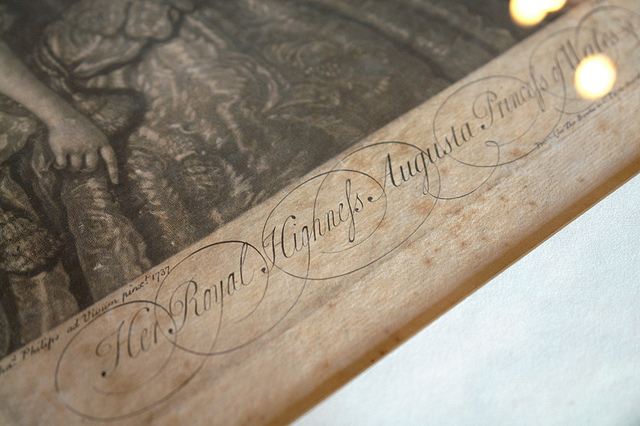
ich find das ja ganz schrecklich. da schreien dich riesige buchstaben in signalfarben an,
du weisst aber nicht wie du es zuordnen sollst, weil du es als parkhausbenutzer nicht so
gewohnt bist und suchst zusätzlich nach schildern. die farben sind eher verstörend,
wenn man ordentlich gestaltete infos sucht und sobald man sich um einen meter
verlenkt sieht das "leitsystem" nur noch nach komischen farbigen flächen aus.
wie ralf schon sagt es ist eher kunst. ich bin mir sicher in dem parkhaus knallt es öfter als vorher ;)
Das Parkhaus finde ich auch zu bunt und nicht besonders schön, und, wenn es dann noch nicht mal zweckmäßig ist, ist es natürlich eher ›suboptimal‹.
Aber die Sache mit dem Point of View finde ich schon cool. Das passt und ist schön gemacht m. E.
In einem Parkhaus kommt man aber auch nur aus einer stark begrenzten Zahl an Richtungen mit relativ leicht kalkulierbarem Blickwinkel auf derartige Beschriftungen zu, insofern ist das Perspektivenproblem wohl nicht sehr groß. Und ein schönes Parkhaus hab ich auch noch nie gefunden, da sind mir die grellen Farbklekser (die es auch so oft in derartigen Einrichtungen gibt) auch schon wurscht.
Hm. Eine kleine Schreibmaschinensammlung habe ich ja schon. Vielleicht sollte ich noch mal umsatteln auf meine alten Tage.
wobei ...
ich glaube ich würde ausrasten wenn ich in 'nem café wäre und da würde
jemand sitzen der wie wild auf seiner schreibmaschine herumhackt.
trotzdem eine schöne idee. paschulke, hurry up! du kannst der erste sein,
der das auf 'nem heidelberger tiegel macht. ;)
Schaut mal, was ich beim Bilderbücherfotografieren für die Illugruppe in meinem Bücherregal entdeckt habe:
Das ist ein Bilderbuch aus den Siebzigern. Und was ist das bitte für ein krasses ß? Das sieht ja aus wie ein versehentliches Versal-Eszett. ;-)
die machen schöne sachen.
Bis ca. 1800 war das ja auch im Englischen noch weit verbreitet.
Aber die Regeln der Verwendung waren anders als im Deutschen.
Vielleicht finden sich hier Hinweise.
Brrr, ich weiß ja: Die beiden Musiker (Thomas Anders, ehemals Modern Talking, und Uwe Fahrenkrog, ehemaliger Nena-Keyboarder) sind 80er, ihre Musik klingt nach den 80ern und das Logo ihrer neuen Kapelle: Ja genau, auch 80er. Und obwohl man dann gestalterisch nichts anderes erwarten dürfte graust es mich …